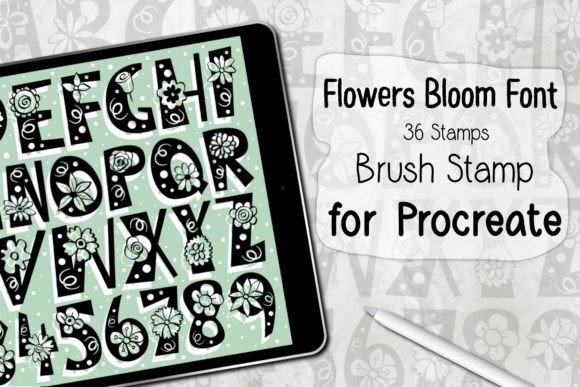
Flowers Bloom Font Procreate Stamp
Trouver les bons éléments de conception peut être un défi, mais Flowers Bloom Font Procreate Stamp propose une collection exceptionnelle qui rehausse instantanément votre travail.
Conçu avec précision, Flowers Bloom Font Procreate Stamp offre des vecteurs nets, une typographie fluide et une licence commerciale pour une tranquillité d'esprit.
Que vous créiez des produits POD (impression à la demande), des invitations de mariage ou des visuels pour les réseaux sociaux, Flowers Bloom Font Procreate Stamp est un choix idéal.